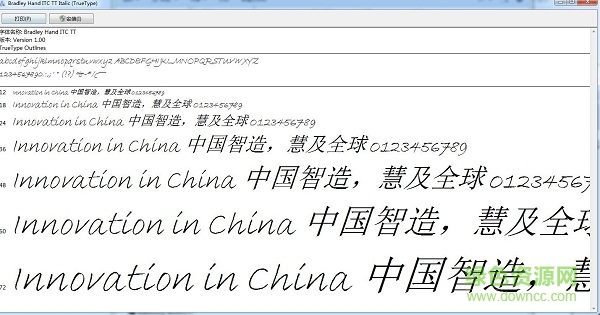
bradley hand itc字體包收錄了常規(guī)體和斜體兩款,這款手寫(xiě)風(fēng)格的字體適合用在電子書(shū)信、賀卡、平面設(shè)計(jì)等領(lǐng)域,整款字體緊湊、流暢,辨識(shí)高,非常實(shí)用,喜歡的朋友快來(lái)下載吧!
1.斜體分兩種,往左或往右傾斜。普通文字處理器都是往右,特殊環(huán)境需要往左,比如印刷版地圖;
2.打字機(jī)、手寫(xiě)等無(wú)法使用斜體的時(shí)候遇到上述情況使用下劃線或引號(hào)加以區(qū)別;
3.表示強(qiáng)調(diào),喚起注意或是書(shū)籍名稱、文章標(biāo)題、船舶名稱等;
4.傳統(tǒng)排版中,漢字一般不使用斜體。電腦的普及給字體變形帶來(lái)了極大方便,才將西文這一習(xí)慣延伸到中文中。